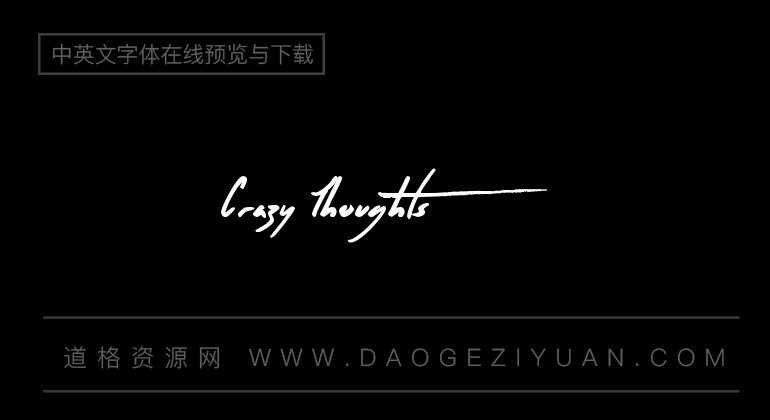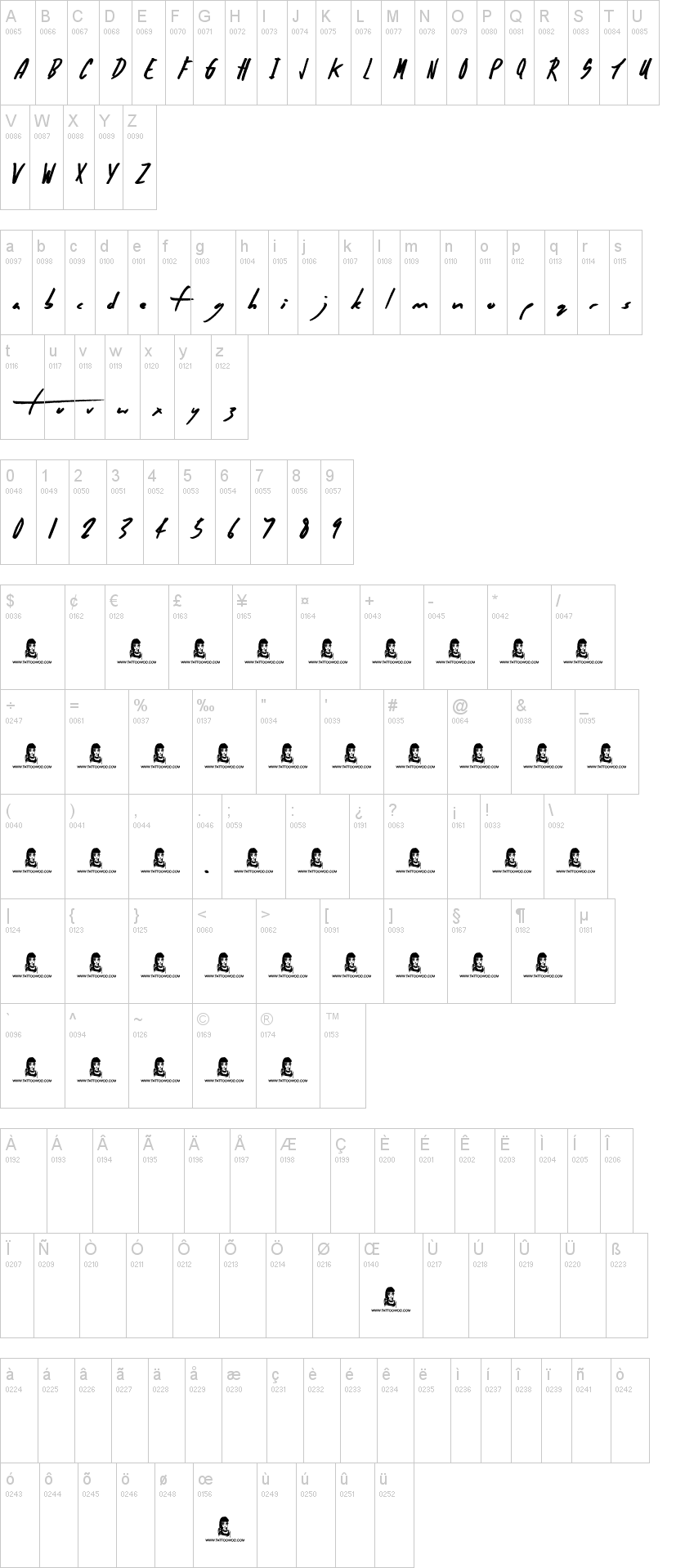
Crazy Thoughts 字体是一种手写风格的字体,它具有非常独特的特点。该字体的字母呈现出自然、随意、奔放的笔画,每个字母都带有一定程度的变形和扭曲,因此看起来非常有趣和疯狂。 Crazy Thoughts 字体常用于印刷或设计中,通常用于需要表现创意和个性的场合。它适合用于海报、标志、包装、书籍封面等设计项目,也可以用于手写风格的印刷品或网页设计等领域。 总体来说,Crazy Thoughts 字体是一种非常有趣和具有创造力的字体,它可以为设计带来很多个性和魅力。内容介绍
Crazy Thoughts是一款非常不错的手写艺术字体,具有很好的视觉感,适合于文化类的宣传设计、商业类品牌的广告和产品包装设计以及个性化文字排版等较多场景。